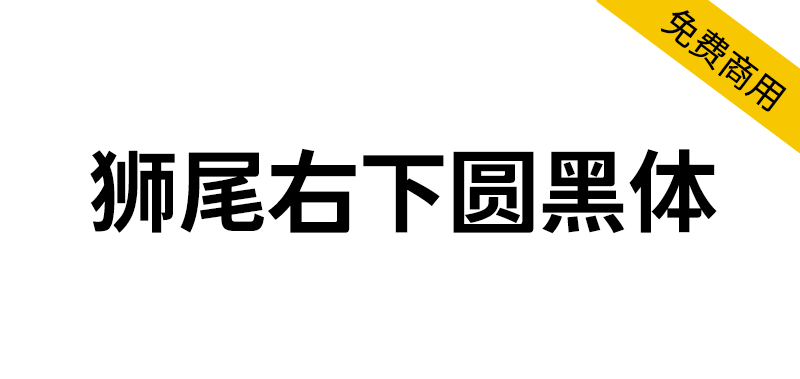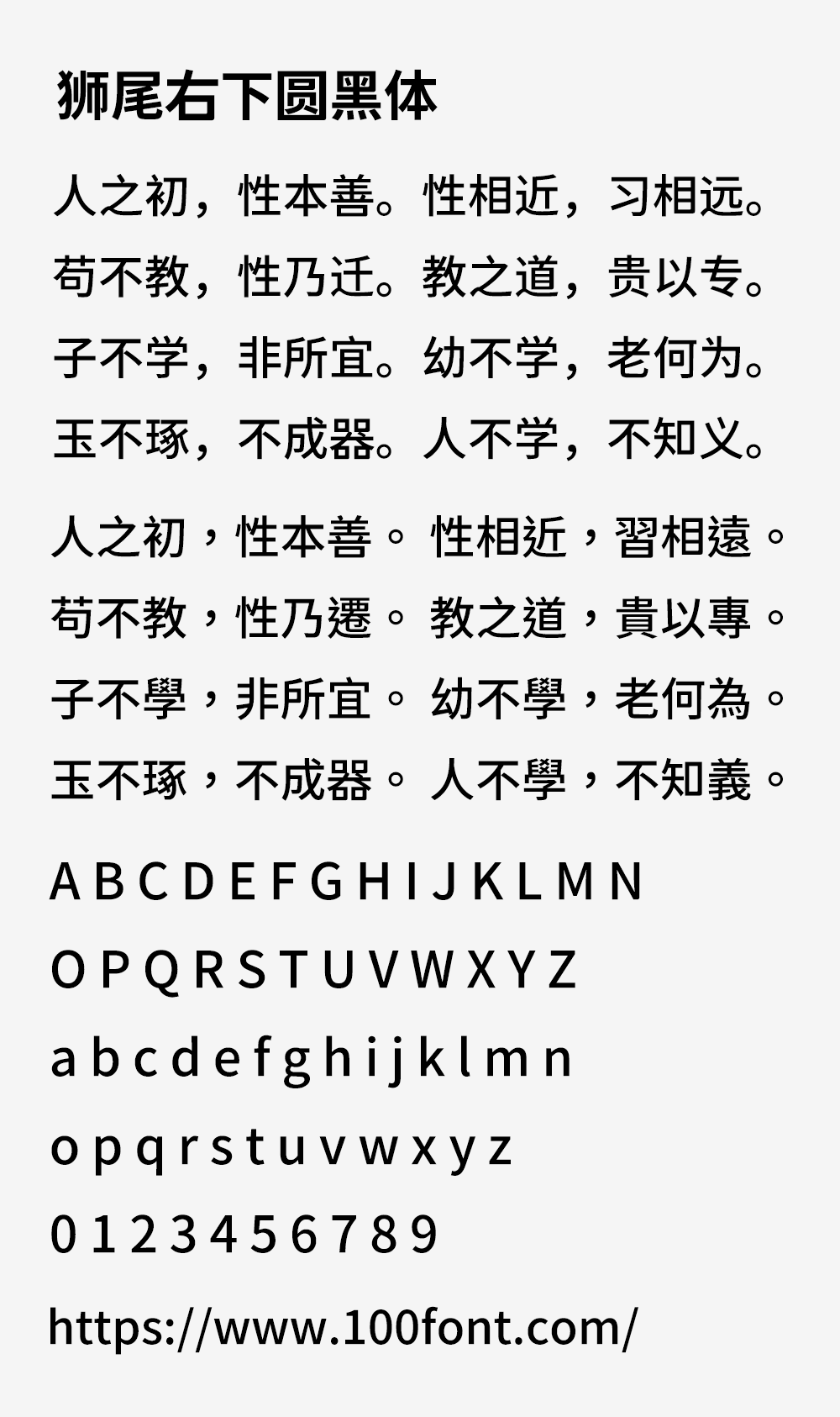
狮尾右下圆黑体基于思源黑体的右下角变圆和拔脚改造,更加简明现代化的字体,和思源黑体一样,有7种字重,支持简体中文、繁体中文、韩文与日文,可以免费商用,欢迎大家自由应用、自由优化、自由改作!
狮尾右下圆黑体与「狮尾右下腿黑体」差别在有没有拔脚,「拔脚」就是会有较少的笔画,例如移除「口」字的左右下角会多出的短线条。有拔脚的字会较圆,但是会造成有些字因直接去掉腿后左右不平衡、左右不对衬的「悬空」问题。改使用「腿」系列字体就不会有这个问题。